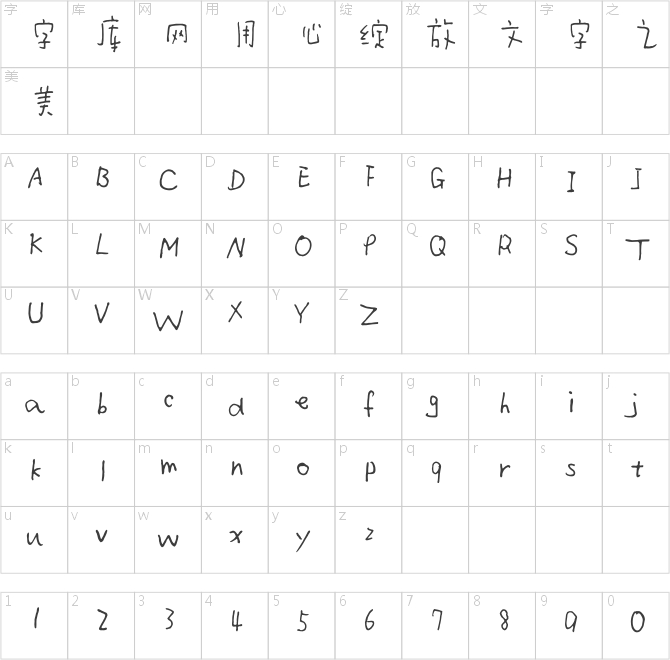
方正王左中右硬筆 簡(jiǎn)
方正王左中右硬筆 簡(jiǎn)字體字庫(kù)是一款讓人賞心悅目、百看不厭的中文字體,適合各類廣告和產(chǎn)品包裝設(shè)計(jì)應(yīng)用,字體大小4.69MB,格式為ttf字體,上傳用戶是昊天金誠(chéng),作者/版權(quán)方為方正字庫(kù)